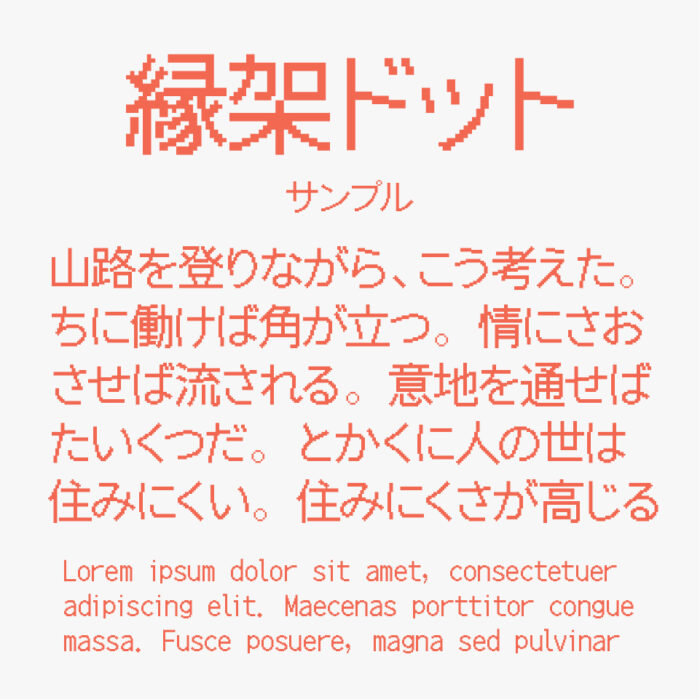
縁架ドットゴシック24 / 縁架ドット明朝24
縁架ドットゴシック24 / 縁架ドット明朝24フォントは、「Noto Sans/Noto Serif」をベースに一文字ずつドット手打ちで制作されたドット風デザインフォントです。
ベースになっている「Noto Sans」「Noto Serif」の安定感に加え、レトロモダンな表情が加わることで、ゲーム感やデジタル感が強くなったフォントです。電光掲示板の文字風デザインなどでも活躍できる素敵なフォントです。
縁架ドットゴシック24フォントはゴシック体/縁架ドット明朝24フォントは明朝体、としてそれぞれが用意されています。